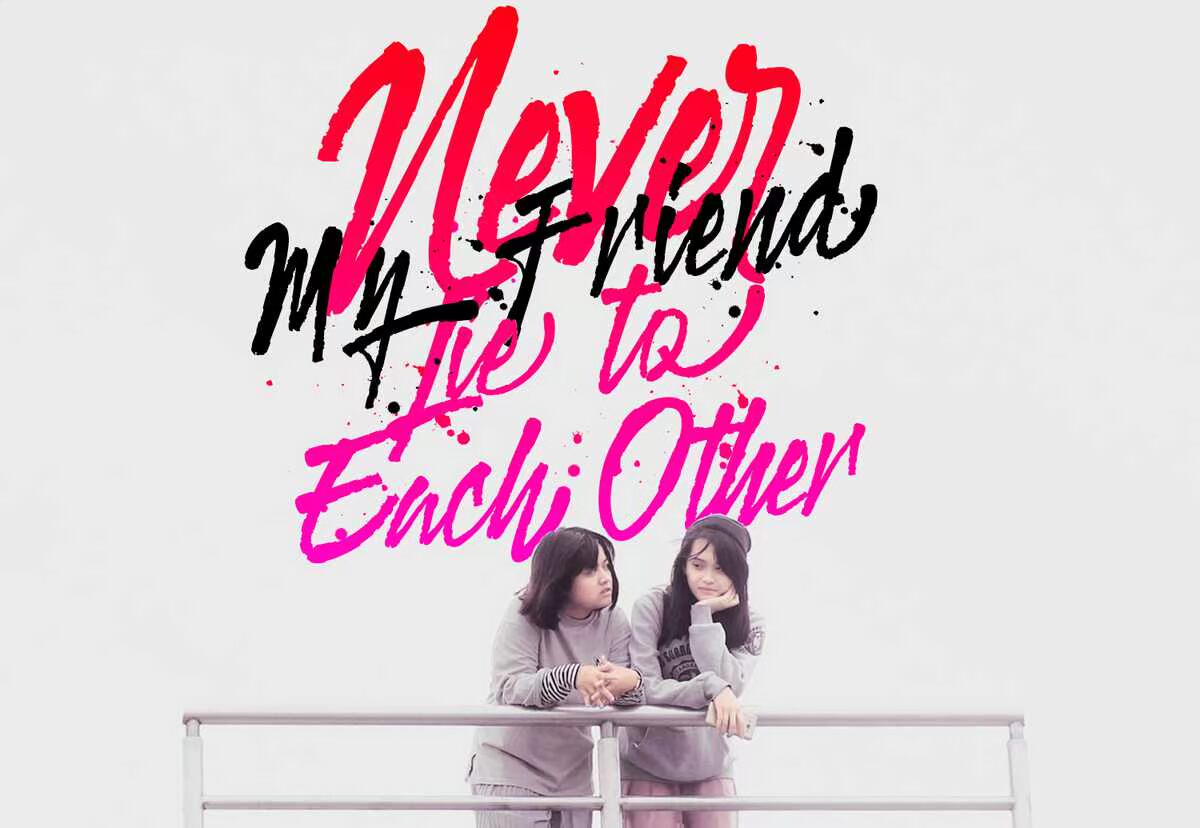
格洛斯特画稿灵感来源于时尚排版风格的Ifestyle。我将其与我的手写风格相结合。让个性化触碰每一条曲线。我希望这能让你从工作中获得灵感。每一条漂亮的基线都能完美地画出对MarkerFont的赞美,以及对Bonusswash的赞美。理想的日志、手写报价、产品包装、标题、海报、商品、,社交媒体和问候卡。格洛斯特画稿灵感来自于时尚风格的Ifestyle。我将其与我的手写字体风格相结合。让个性化触碰每一条曲线。我希望这能让你从工作中获得灵感。每一条宽大的基线都有完美的修饰、恭维的Markerfont,以及完美的Bonusswash。理想的日志、手写引号、产品包装、标题、,海报、商品、社交媒体和问候卡。